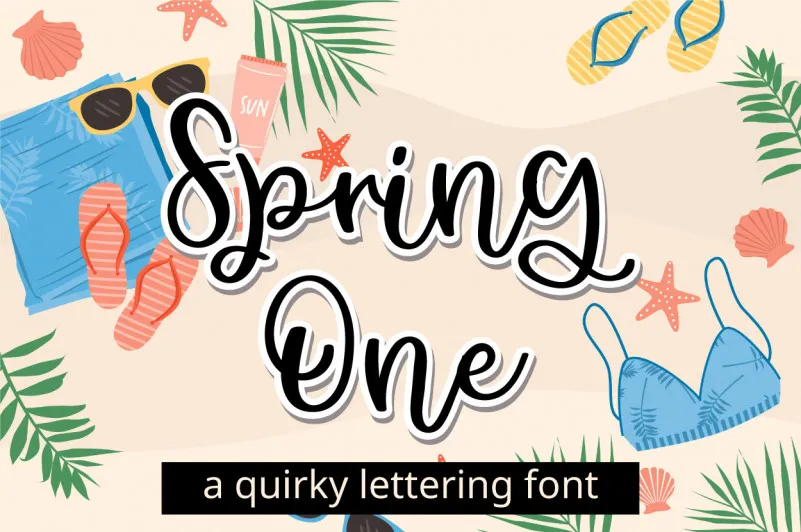
Spring One Font
Descubra a elegância autêntica da ‘Spring One Font’, uma fonte à mão livre criada pelo talentoso designer sugiharto1790. Esta fonte é perfeita para quem procura um estilo natural e envolvente, capaz de dar vida aos seus projetos digitais. As linhas delicadas e os traços suaves da ‘Spring One Font’ evocam o frescor das manhãs brilhantes do sul do Brasil. Seu uso cria uma atmosfera amigável que pode ser aplicada em cartazes publicitários, materiais de embalagem ou design gráfico em geral. Ao utilizar esta fonte à mão livre, você se beneficia da sua versatilidade e originalidade, além de concordar com as regras do nosso Acordo de Uso do Produto. Nesse sentido, a ‘Spring One Font’ é mais que uma escolha visual; ela é um complemento que transforma ideias em realidade.